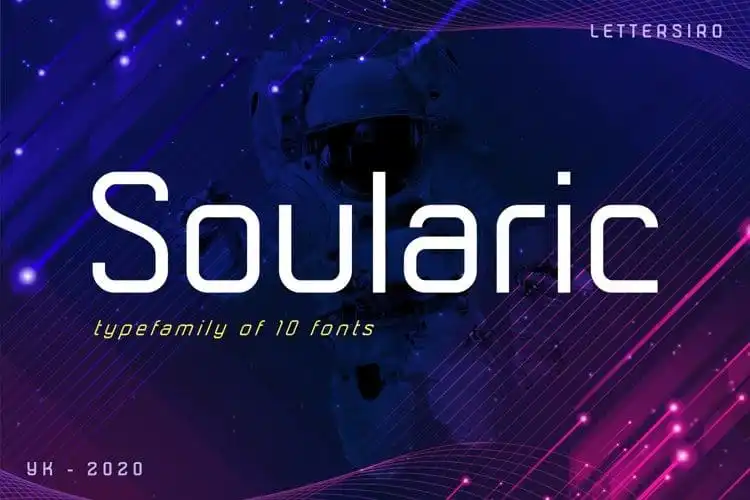
Soularic Sans Serif Font – Fonte Grátis
Soularic Sans Serif Font
A fonte Soularic Sans Serif é uma escolha perfeita para designers atentos às nuances do futuro. Seu design robusto e desafiador introduz nuances inovadoras, adequadas a um vasto range de projetos gráficos. Com essa fonte, você pode incorporar sua imaginação futurista em qualquer projeto design que possa ter, seja para o título, tipografia ou mesmo para embalagens, materiais publicitários ou websites. Especialmente ideal para entusiasmadas ideias de moda e decoração, Soularic Sans Serif é a fonte perfeita para tornar seus designs mais modernos e profissionais. Não deixe que outras futurísticas fontes sejam a única opção disponível. Adquira-a agora para um design ainda mais inovador e contemporâneo.